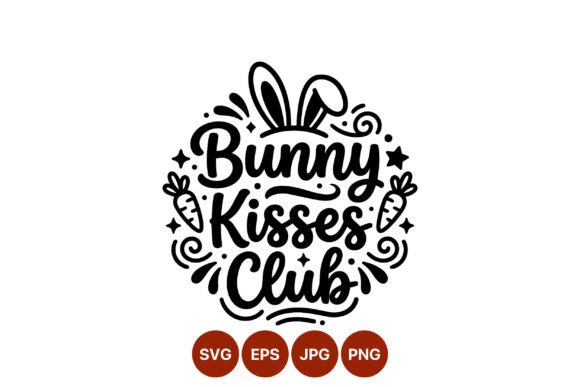
Bunny Kisses Club Cute Hand Lettering
Trouver les bons éléments de conception peut être un défi, mais Bunny Kisses Club Cute Hand Lettering propose une collection exceptionnelle qui rehausse instantanément votre travail.
Conçu avec précision, Bunny Kisses Club Cute Hand Lettering offre des vecteurs nets, une typographie fluide et une licence commerciale pour une tranquillité d'esprit.
Que vous créiez des produits POD (impression à la demande), des invitations de mariage ou des visuels pour les réseaux sociaux, Bunny Kisses Club Cute Hand Lettering est un choix idéal.